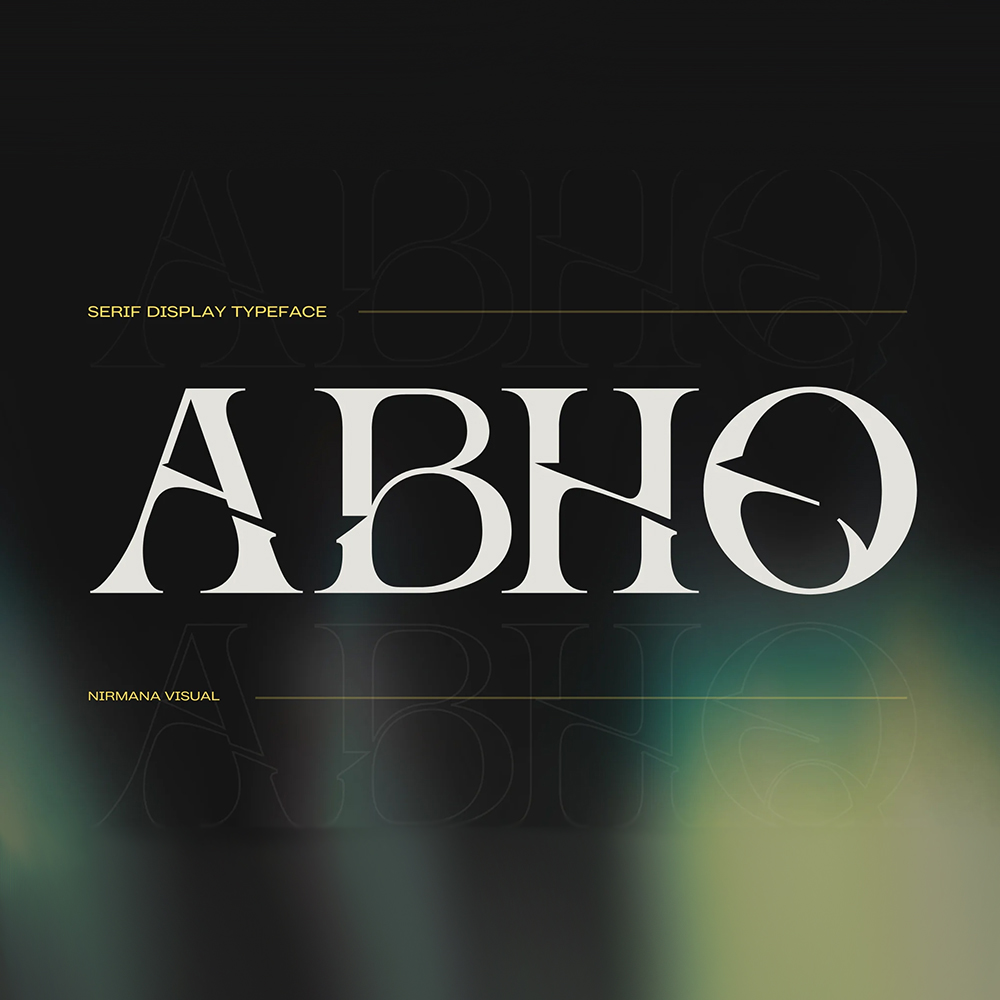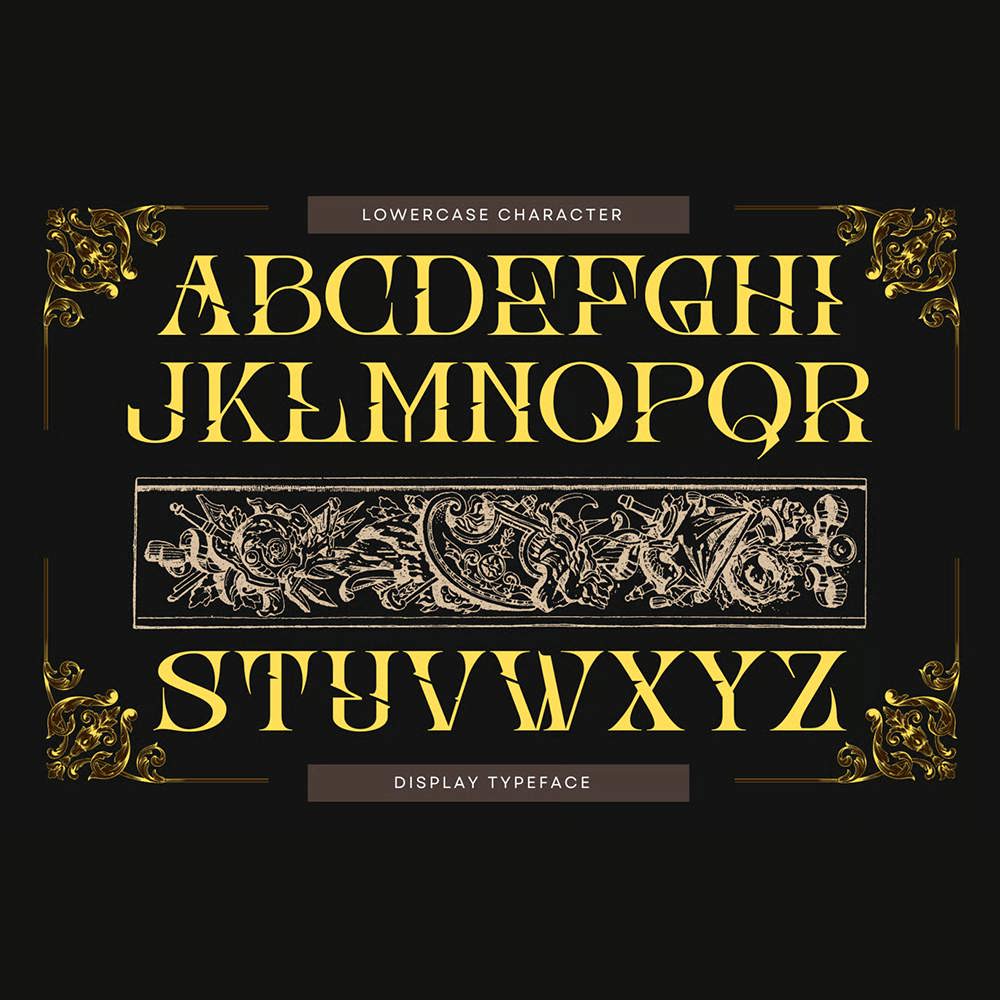
فونت پرمیوم و انگلیسی Abho Luxury Font هارمونی تایپوگرافی زیبایی را برای انواع پروژههای طراحی، از جمله لوگو و برندسازی، پستهای رسانههای اجتماعی، تبلیغات و طراحی محصولات ارائه میدهد که با استفاده از این فونت فوقالعاده، نتایج تایپوگرافی، حروفنگاری فوقالعادهای میتوانید خلق کنید.
مزایای استفاده از فونت لاتین Abho Luxury چیست؟